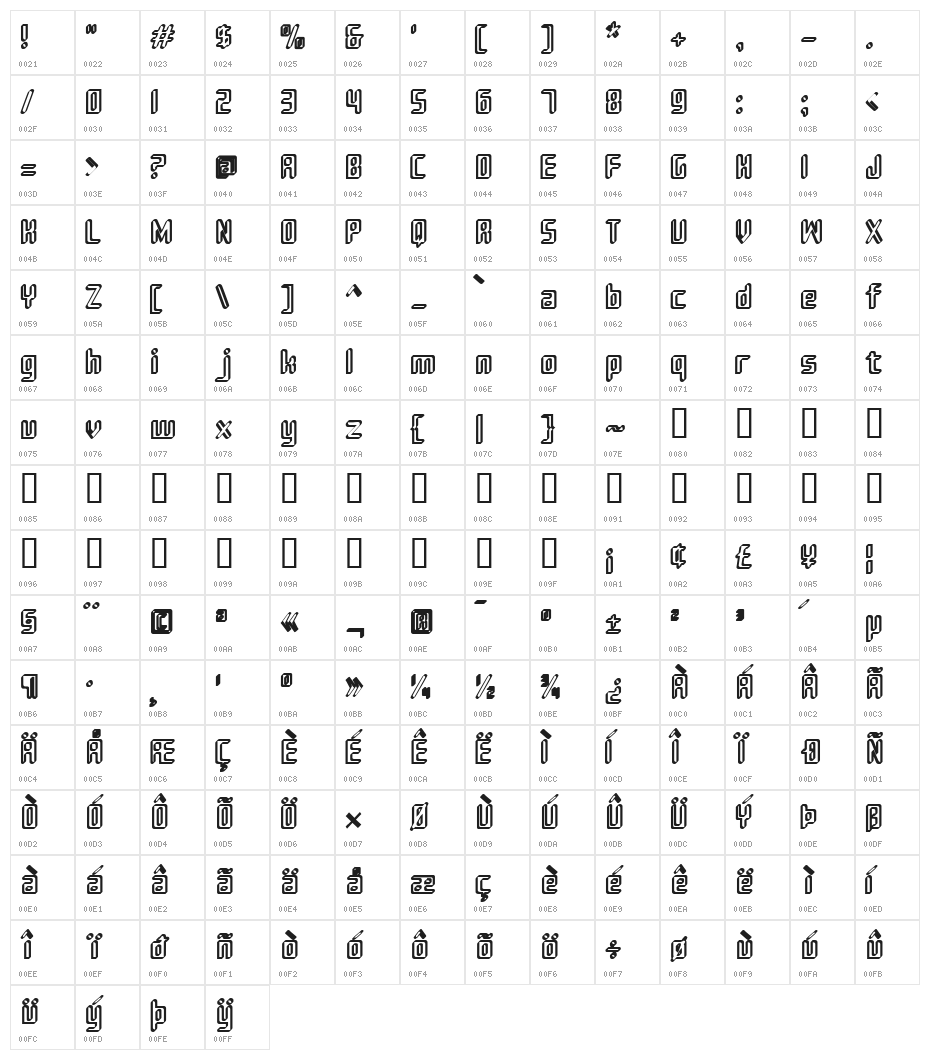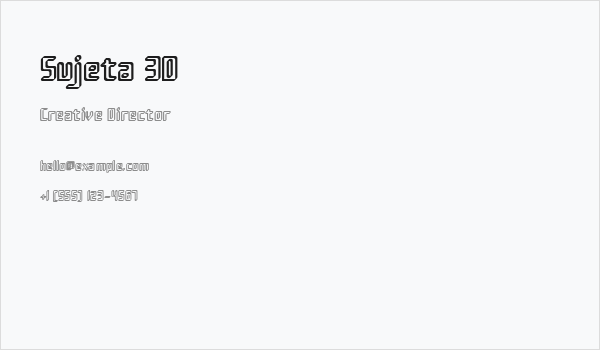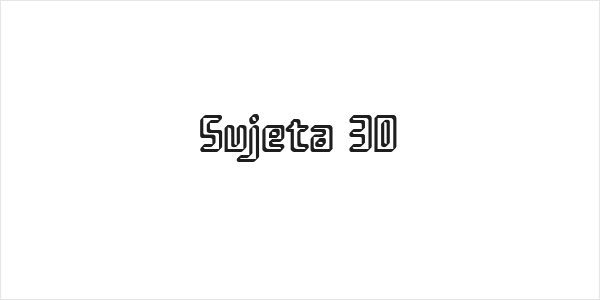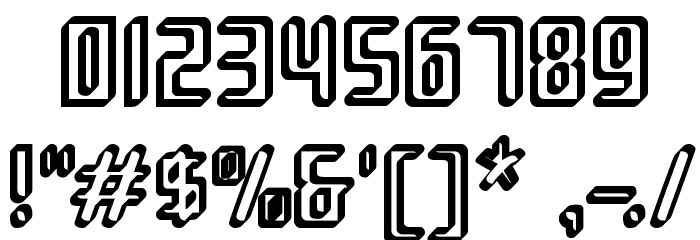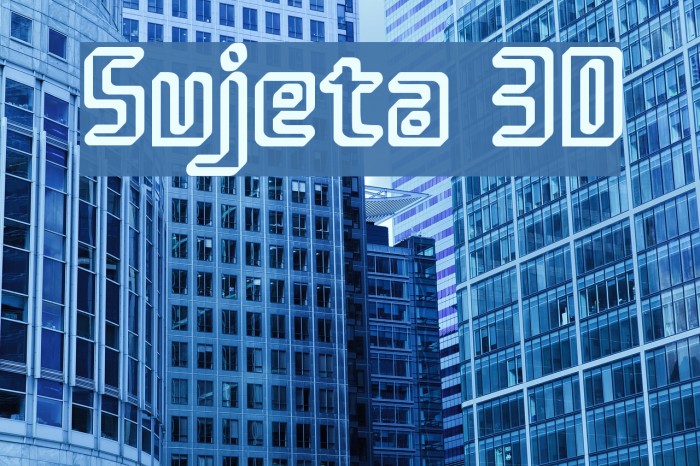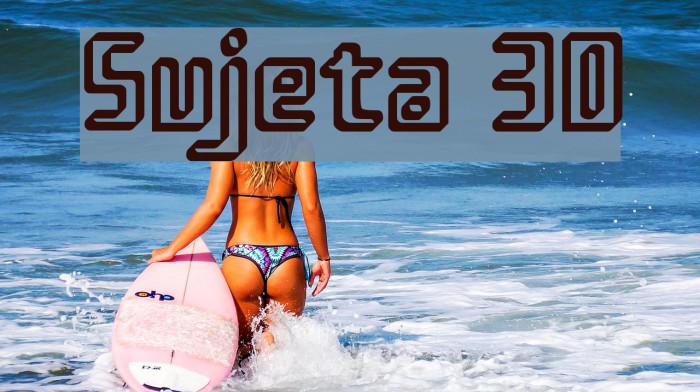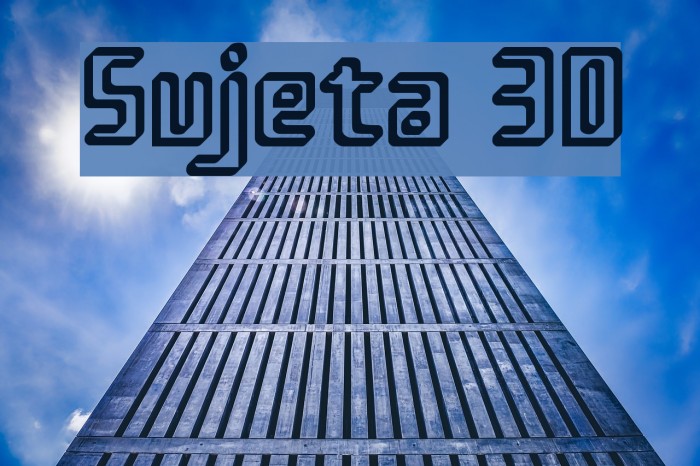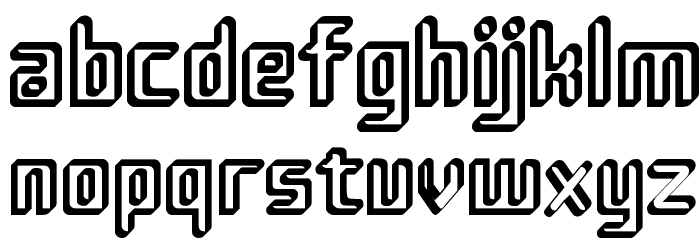
Sujeta 3D Font
| Caso d'uso | Logos, Posters, Headlines |
| Progetti proposti | Ideal for logos, posters, video game graphics, and any project needing a striking, modern aesthetic. |